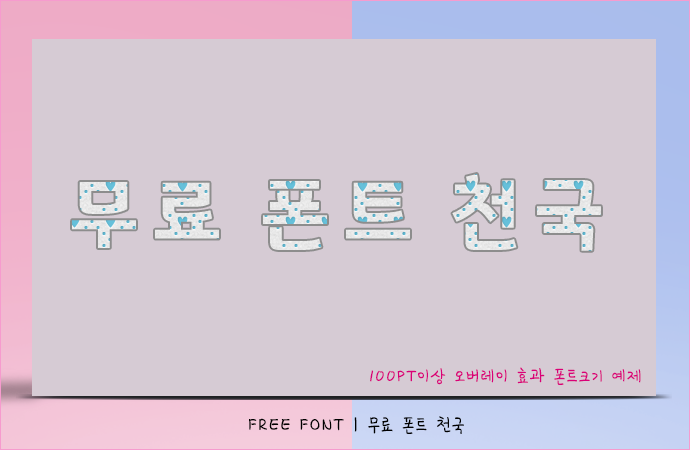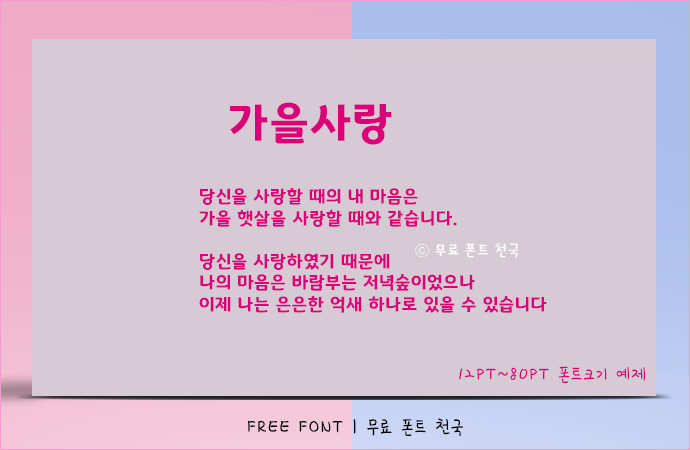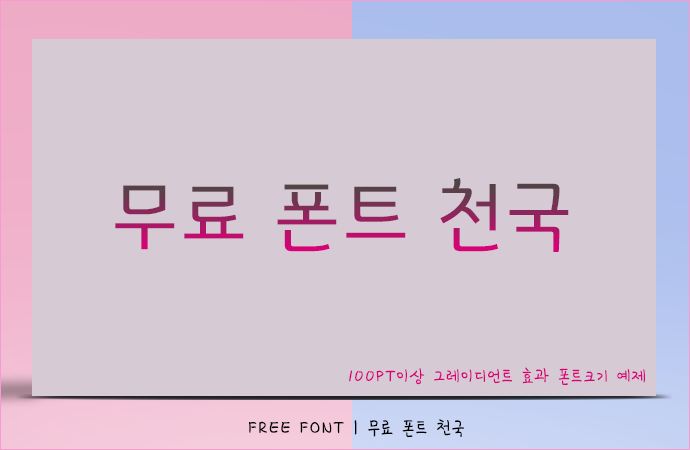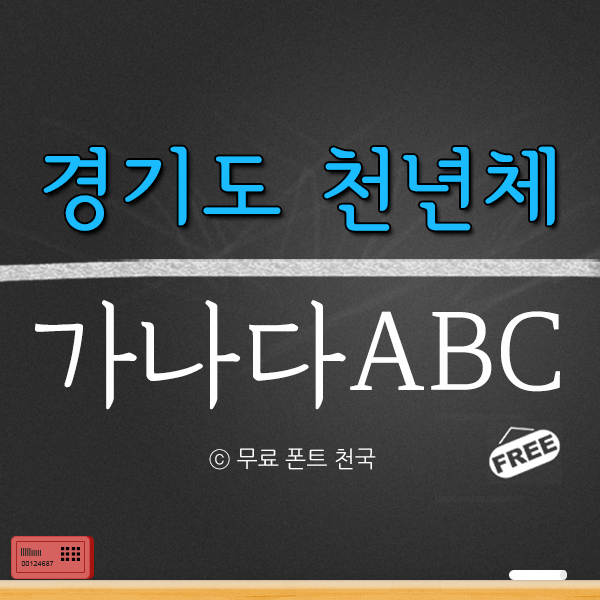
굵직하고 또박또박 바른 경기도 천년체 폰트
경기도 천년체 폰트 정보
또박또박 굵고 강직한 느낌이 서체로 표현한 경기도 천년체 폰트입니다. 누구나 제한 없이 무료로 사용 가능한 프리웨어 폰트입니다. 경기도 천년체 압축파일 안에는 경기처년바탕체, 경기천년 제목체등 총 6개의 폰트가 포함되어 있습니다. 천년체 하나로 굵고 가느다란 느낌의 서체를 표현할 수 있습니다. 자세한 사항은 아래 예제를 통해 확인하세요.
경기도 천년체 폰트 # 미리보기
경기도 천년체 폰트, 12~80PT 크기로 적용한 효과
경기도 천년체 폰트, 100PT 크기 이상으로 작업한 오버레이 효과
경기도 천년체 폰트, 100PT 크기 이상으로 작업한 그레이언트 효과